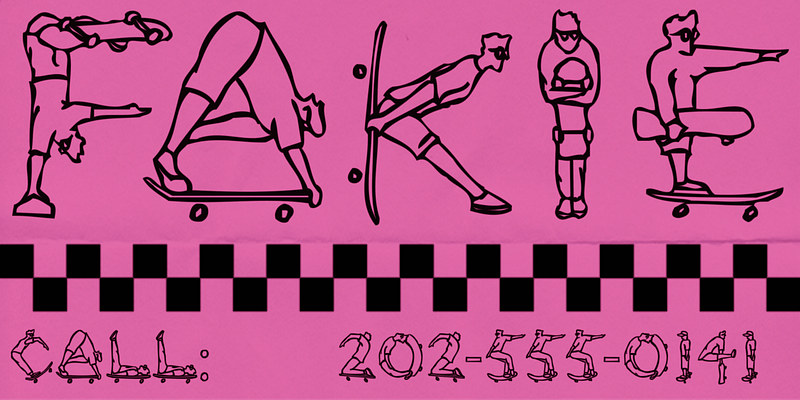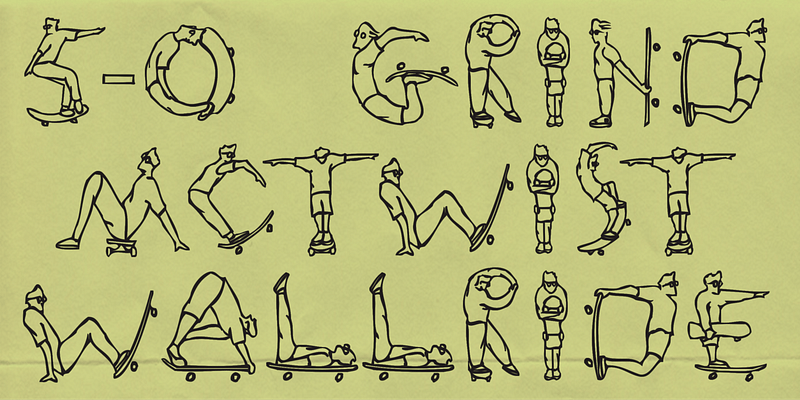
John Ritter, graphiste chez Adobe, a adapté Rad d’un alphabet de skateboard qu’il a créé à l’université pour un devoir. Dans Rad, il a capturé l’esprit « pas de règles » de la communauté du skateboard, qu’il rejoignait quand il n’étudiait pas.